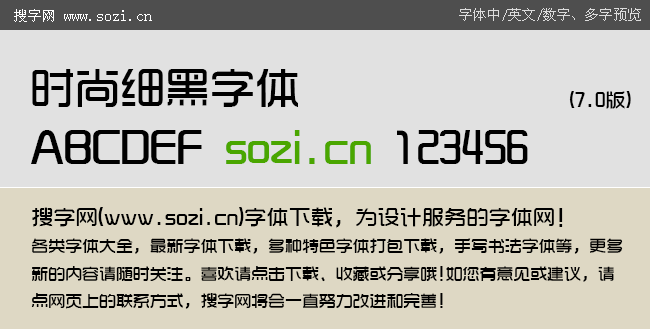
時(shí)尚細(xì)黑字體
搜字網(wǎng)提供一款時(shí)尚細(xì)黑字體中文藝術(shù)字體下載,該字體由時(shí)尚傳媒集團(tuán)自主設(shè)計(jì),是國(guó)內(nèi)首家以企業(yè)名稱命名的規(guī)范字體,時(shí)尚細(xì)黑字體整體字形筆畫均衡,風(fēng)格現(xiàn)代,字體方中帶圓,端莊雅致,簡(jiǎn)約時(shí)尚。適宜用于時(shí)尚類企業(yè)形象、產(chǎn)品名稱和廣告標(biāo)題類用字。